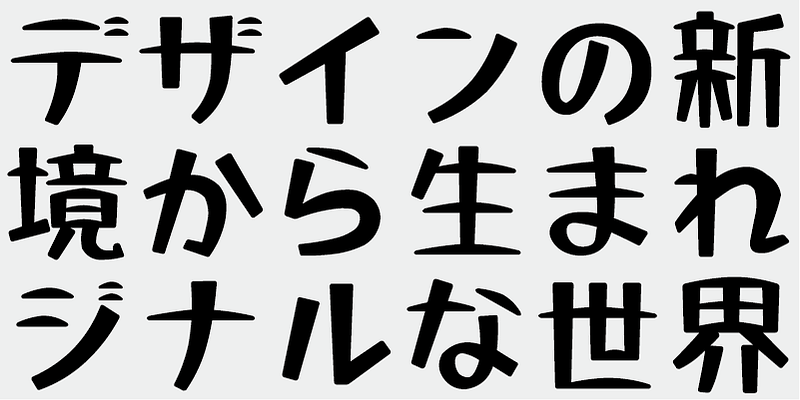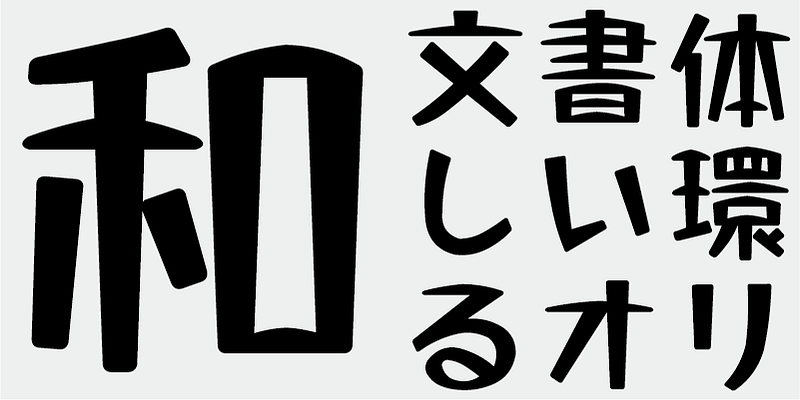
Cette police rétro vous rappellera les pieds des radiateurs électriques traditionnels japonais kotatsu.
Cette police comprend les 1 000 principaux caractères kanji, choisis dans les tables de fréquence des caractères établis par les sociétés de presse, les maisons d’édition et les instituts de recherche linguistique, ainsi que 206 caractères kana et signes de ponctuation.
Dans la production de polices japonaises d’aujourd’hui, les 7 000 caractères de la norme JIS sont considérés comme essentiels. Mais toutes les polices ont-elles vraiment besoin de 7 000 caractères ? À l’ère de la phototypie, on utilisait beaucoup moins de caractères. FONT1000, un groupe de typographes indépendants, a commencé par se focaliser sur cette simple question. Nous avons sélectionné le minimum de 1 000 caractères kanji (idéographiques) nécessaires pour la composition en japonais et créé activement des polices pour les prendre en charge. Ce jeu de 1 000 caractères kanji a été créé en étudiant des données de fréquence des caractères compilées par des sociétés de presse, des maisons d’édition et des organismes de recherche linguistique, etc. Il comprend également des caractères syllabiques kana et des signes de ponctuation. FONT1000 a été créée en 2001 avec 25 designers et 25 polices de caractères. Aujourd’hui, nous avons 130 polices et comptons désormais près de 40 membres, ce qui permet de travailler sur des polices avec plus de caractères.